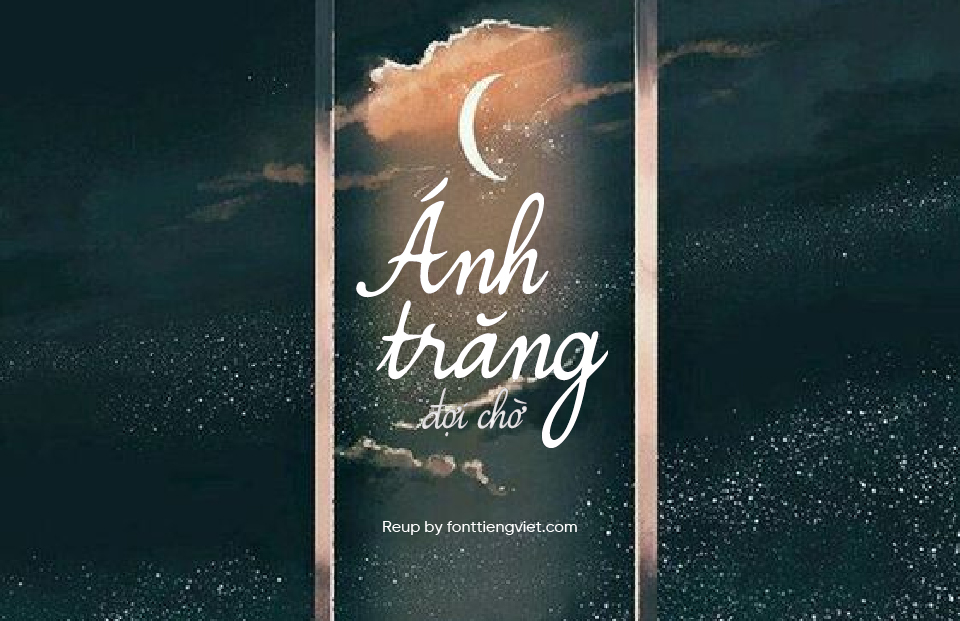
Giới thiệu về Font tiếng Việt Simplesnails
Trong thế giới đồ họa hiện đại, việc lựa chọn một bộ Font Chữ phù hợp đóng vai trò quyết định đến tính thẩm mỹ của sản phẩm. Font tiếng Việt Simplesnails là một lựa chọn tuyệt vời dành cho những ai yêu thích phong cách viết tay nhẹ nhàng, uyển chuyển nhưng không kém phần tinh tế. Được thiết kế với những đường nét bo tròn mềm mại, bộ font này mang lại cảm giác gần gũi và thân thiện cho người xem. Đặc biệt, phiên bản Font tiếng Việt Simplesnails đã được tối ưu hóa đầy đủ hệ thống dấu thanh tiếng Việt, giúp các bạn học sinh và giáo viên dễ dàng ứng dụng vào công việc soạn thảo giáo án hay thiết kế bài thuyết trình sinh động.
Đặc điểm nổi bật của Font tiếng Việt Simplesnails
Phong cách thiết kế độc đáo
Font tiếng Việt Simplesnails nổi bật với cấu trúc các chữ cái mô phỏng nét vẽ thủ công tự nhiên. Khoảng cách giữa các ký tự được căn chỉnh tỉ mỉ, giúp văn bản duy trì độ đọc tốt ngay cả khi sử dụng ở kích thước nhỏ. Đây là giải pháp hoàn hảo cho các dự án thiết kế thiệp mời, trang trí sổ tay (bullet journal) hoặc làm tiêu đề cho các video học tập trực tuyến.
Khả năng tương thích cao
Để phát huy tối đa vẻ đẹp của Font tiếng Việt Simplesnails, bạn nên kết hợp nó với các màu sắc pastel hoặc nền giấy nhám để tạo hiệu ứng vintage. Việc sở hữu một bộ font việt hóa chất lượng sẽ giúp bài làm của học sinh trở nên ấn tượng hơn trong mắt thầy cô. Hãy truy cập ngay để tải về Font Miễn Phí, Font Việt Hóa, Font tiếng Việt Simplesnails và bắt đầu hành trình sáng tạo của riêng mình nhé.